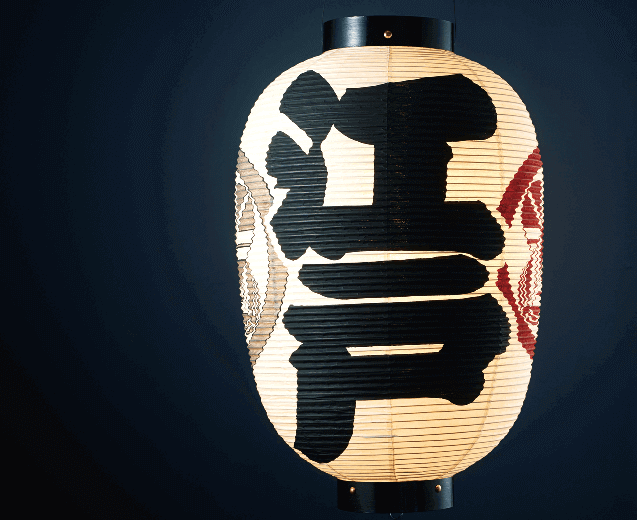
江户文字之「提灯文字」
提灯文字(ちょうちんもじ)是江户文字分类中的一种,顾名思义就是在提灯上使用的文字。常见于日式串烧亭外,也被用于海报、传单和千社札(姓名贴纸)等。
提灯文字的绘制是基于书籍字体,所以很容易阅读,笔画厚重却不拖沓,布白匀称,即使从远处看也不会糊作一团无法识别。
提灯文字不是简单的一步绘制完成,而是前期先用用铅笔勾线,然后用面刷绘制轮廓,接着用圆刷、平刷填充内部,最后增加一些笔画装饰。